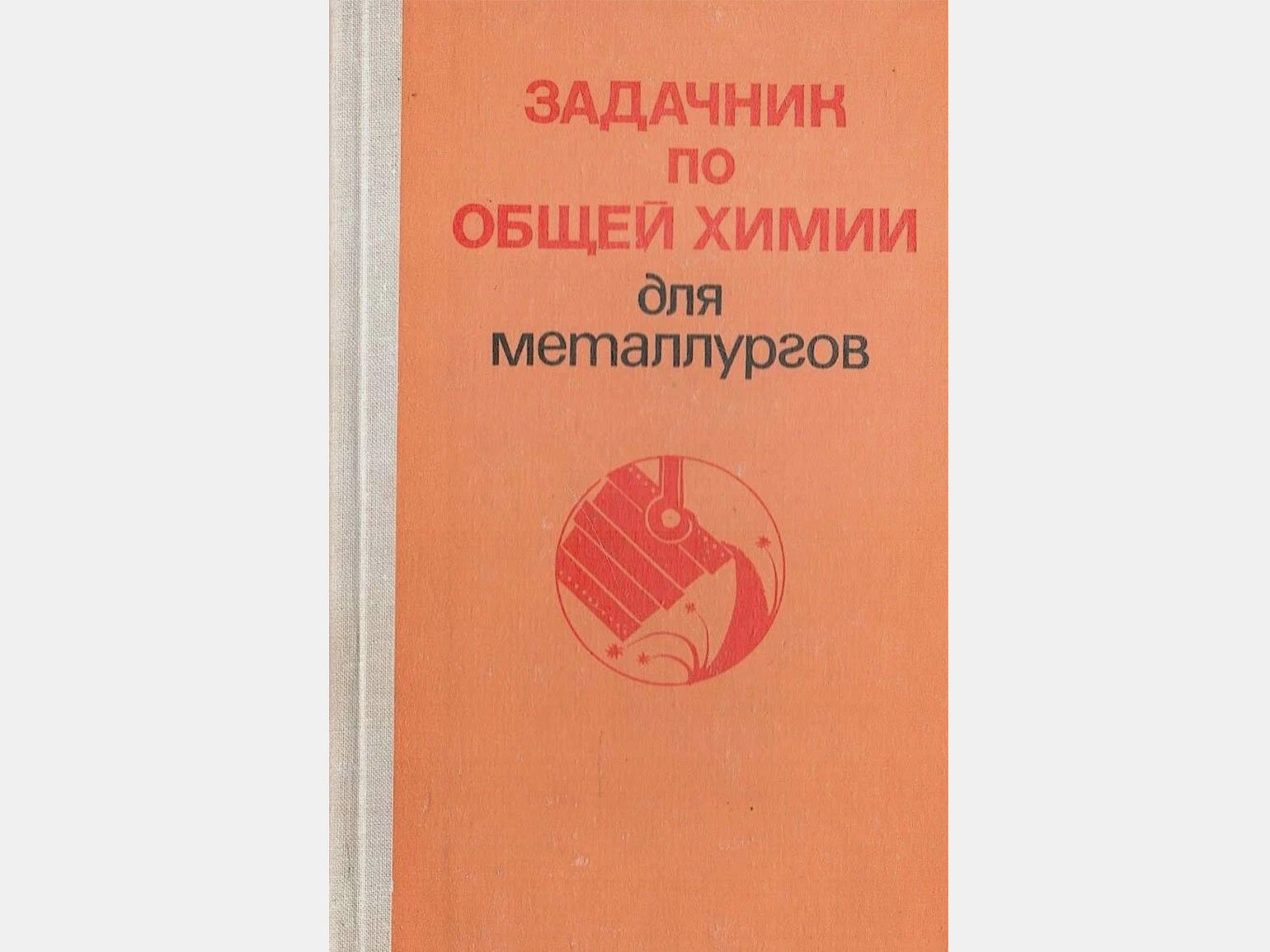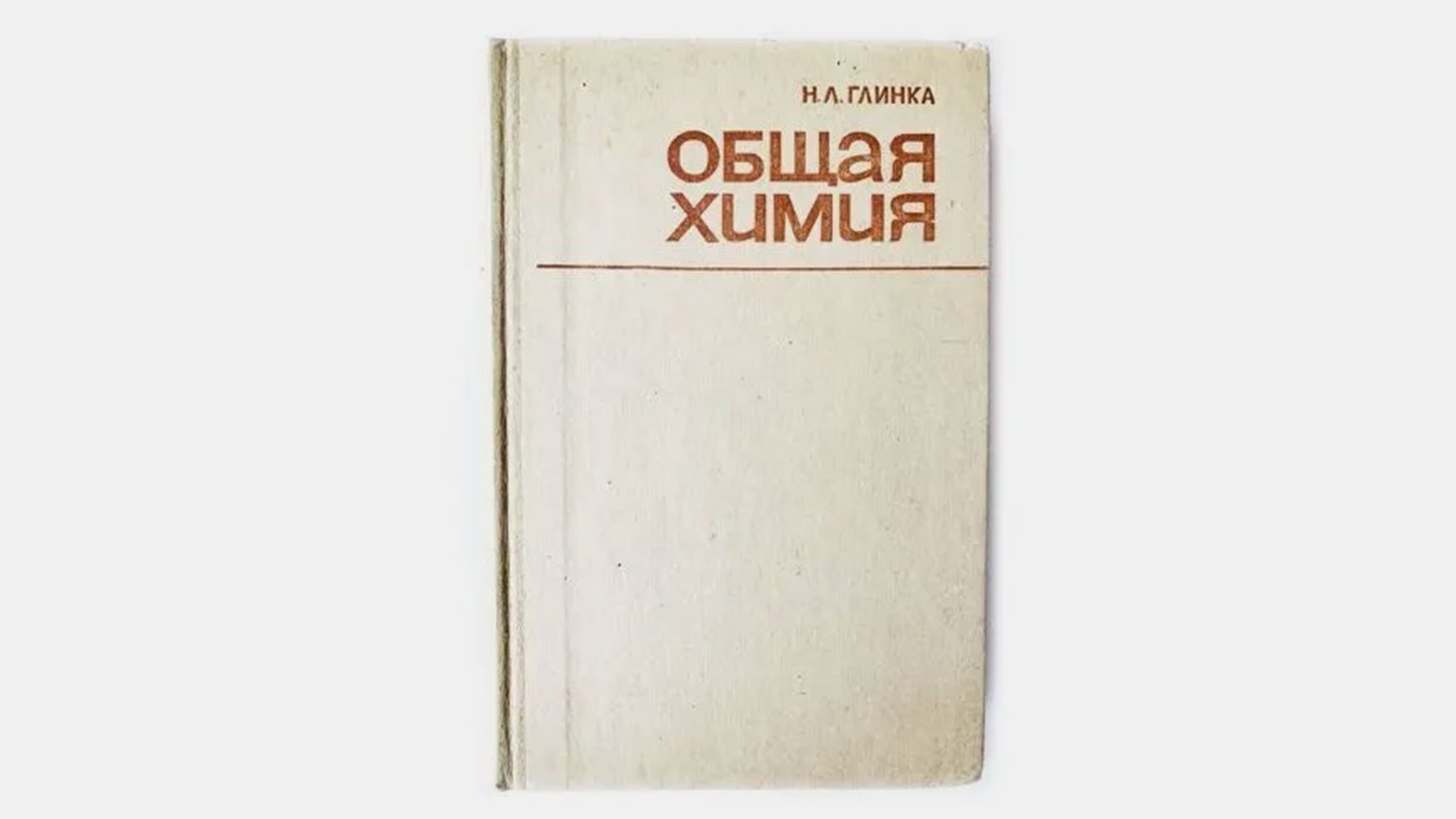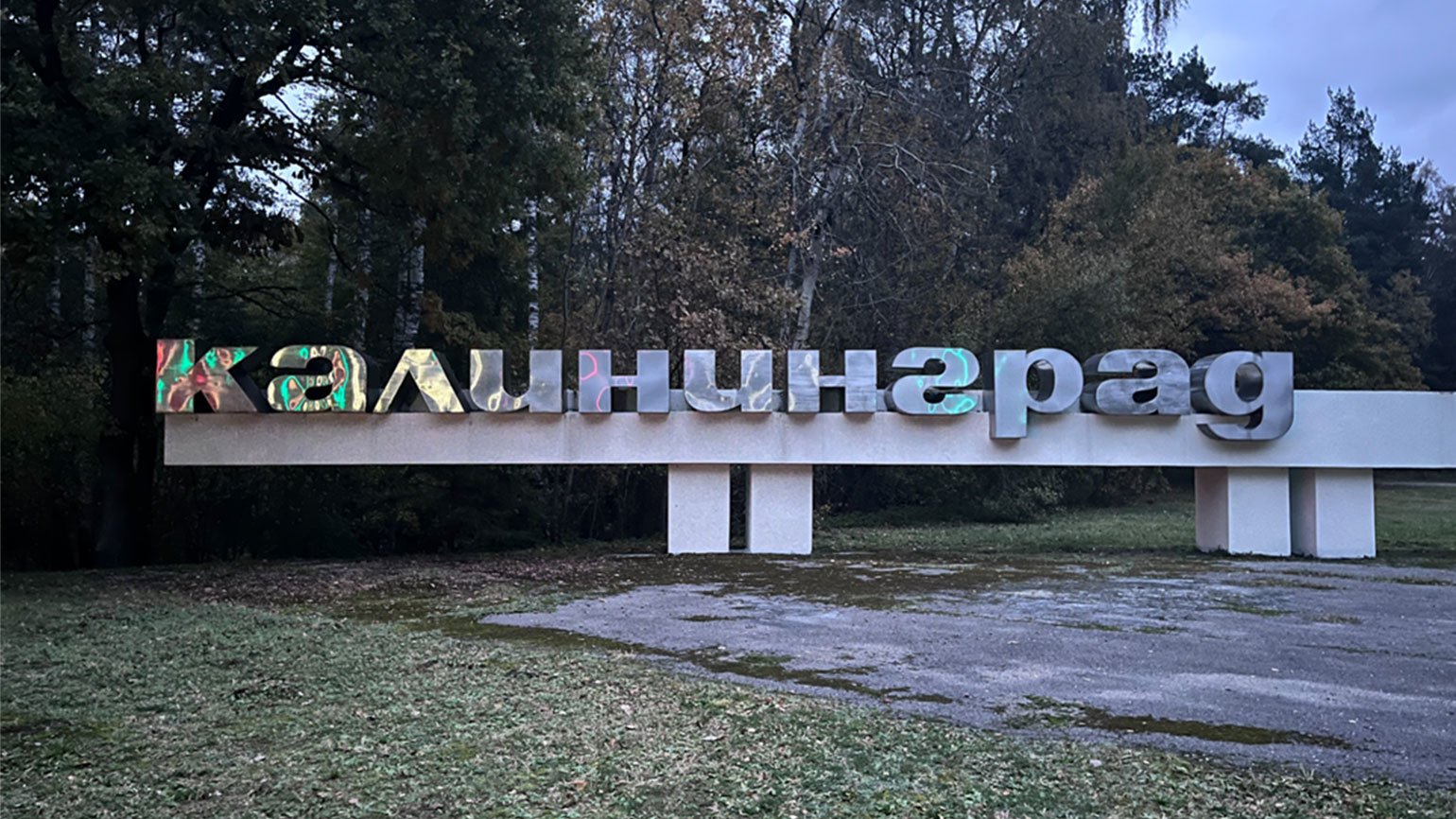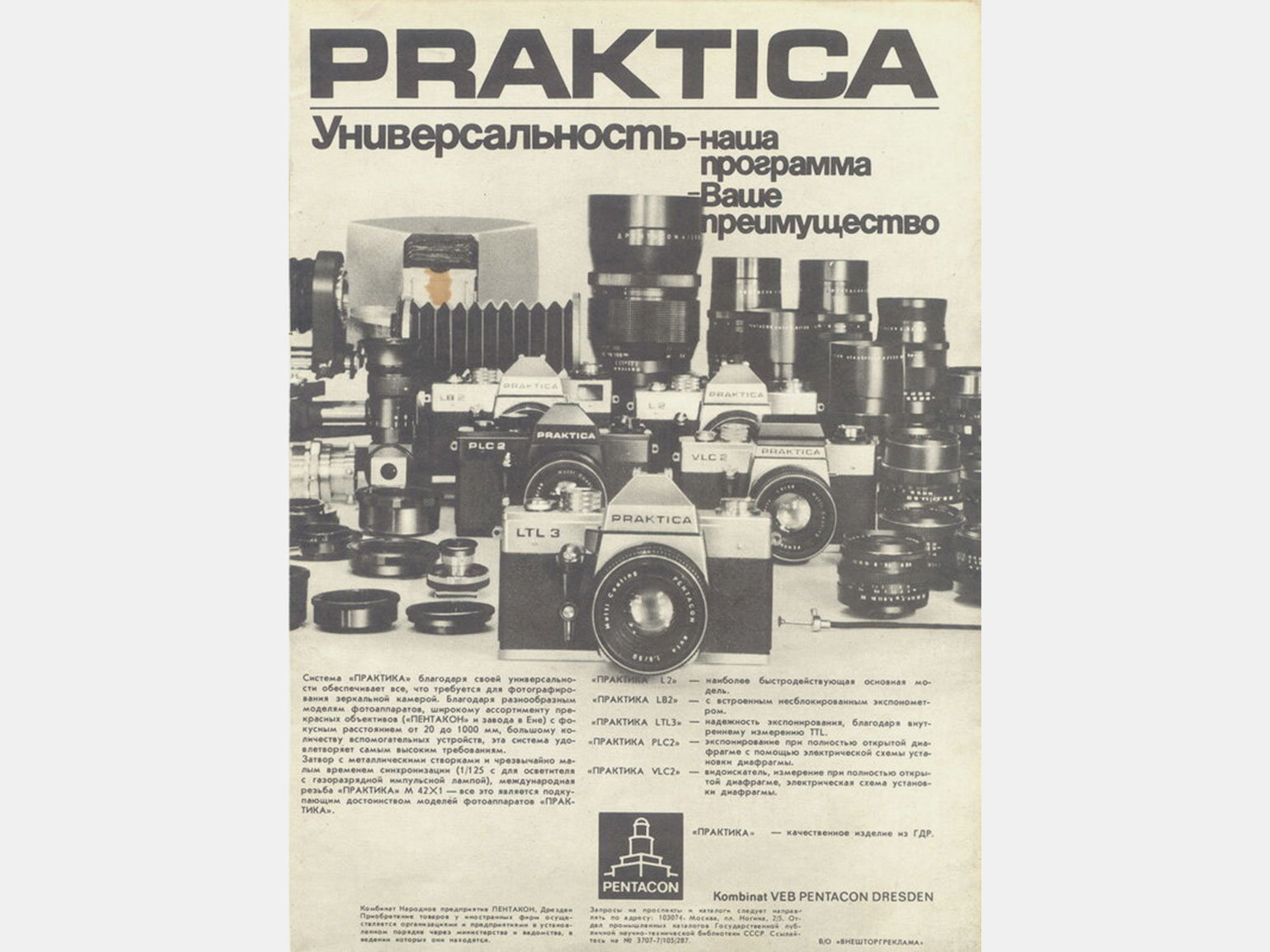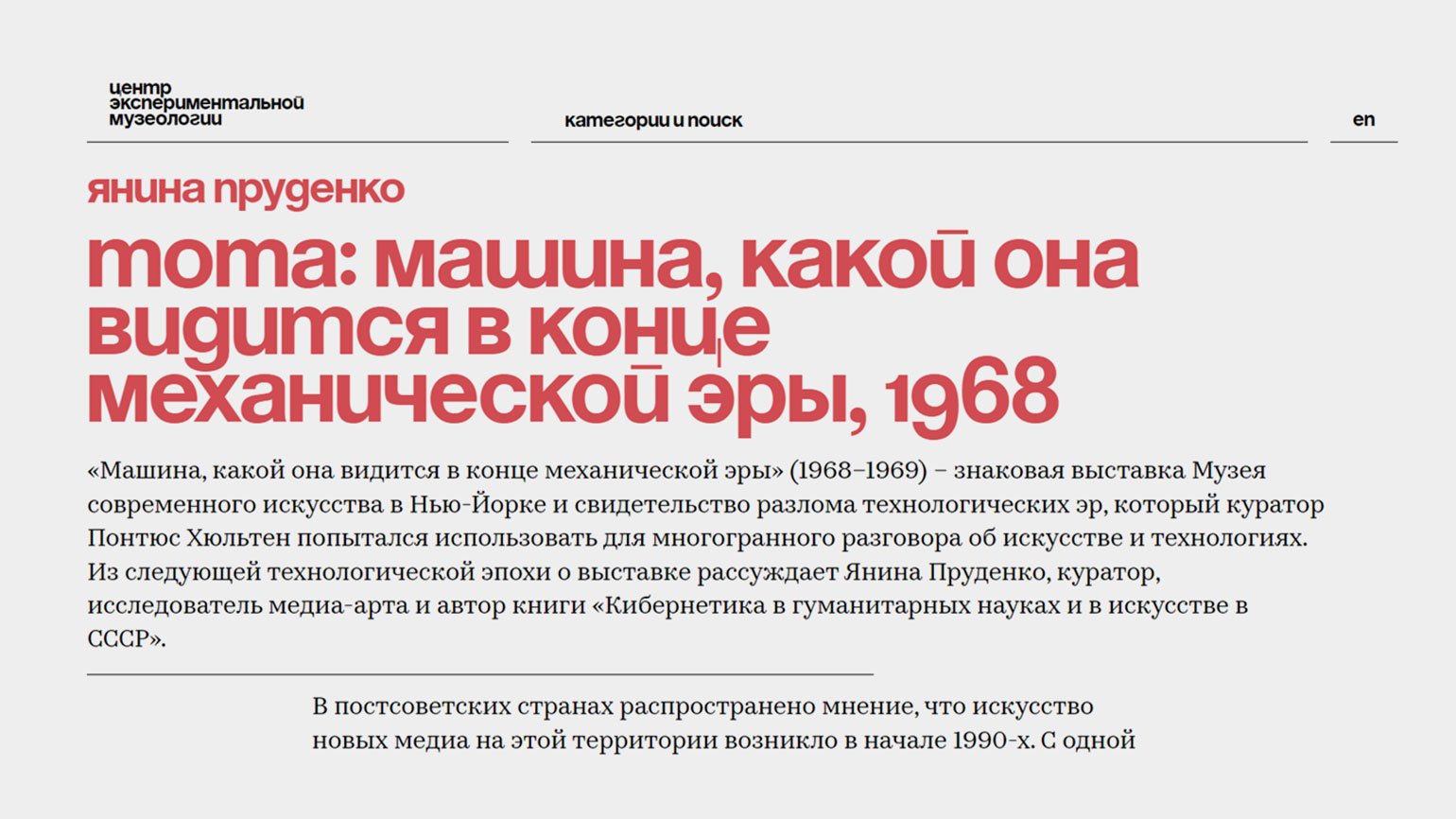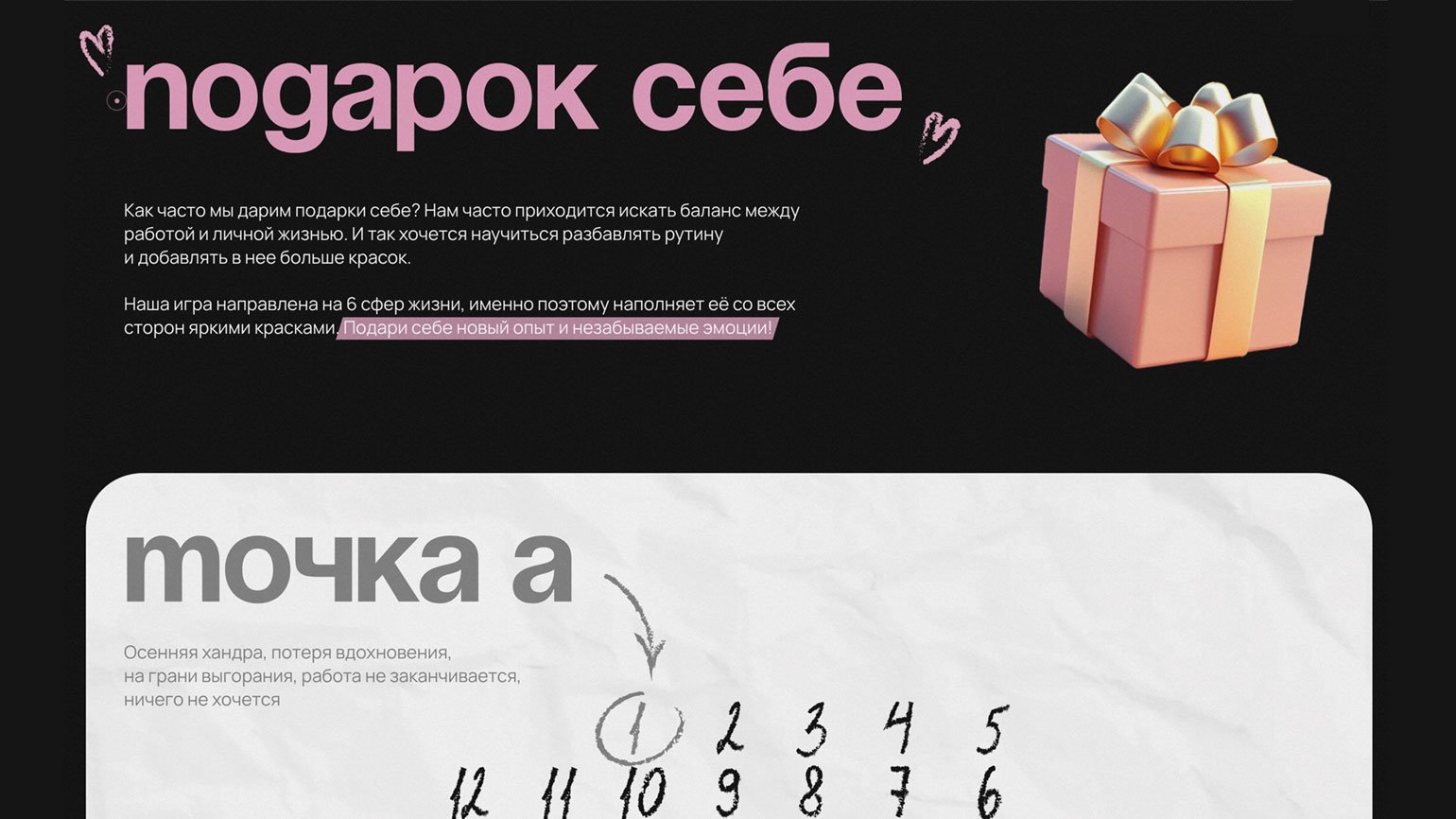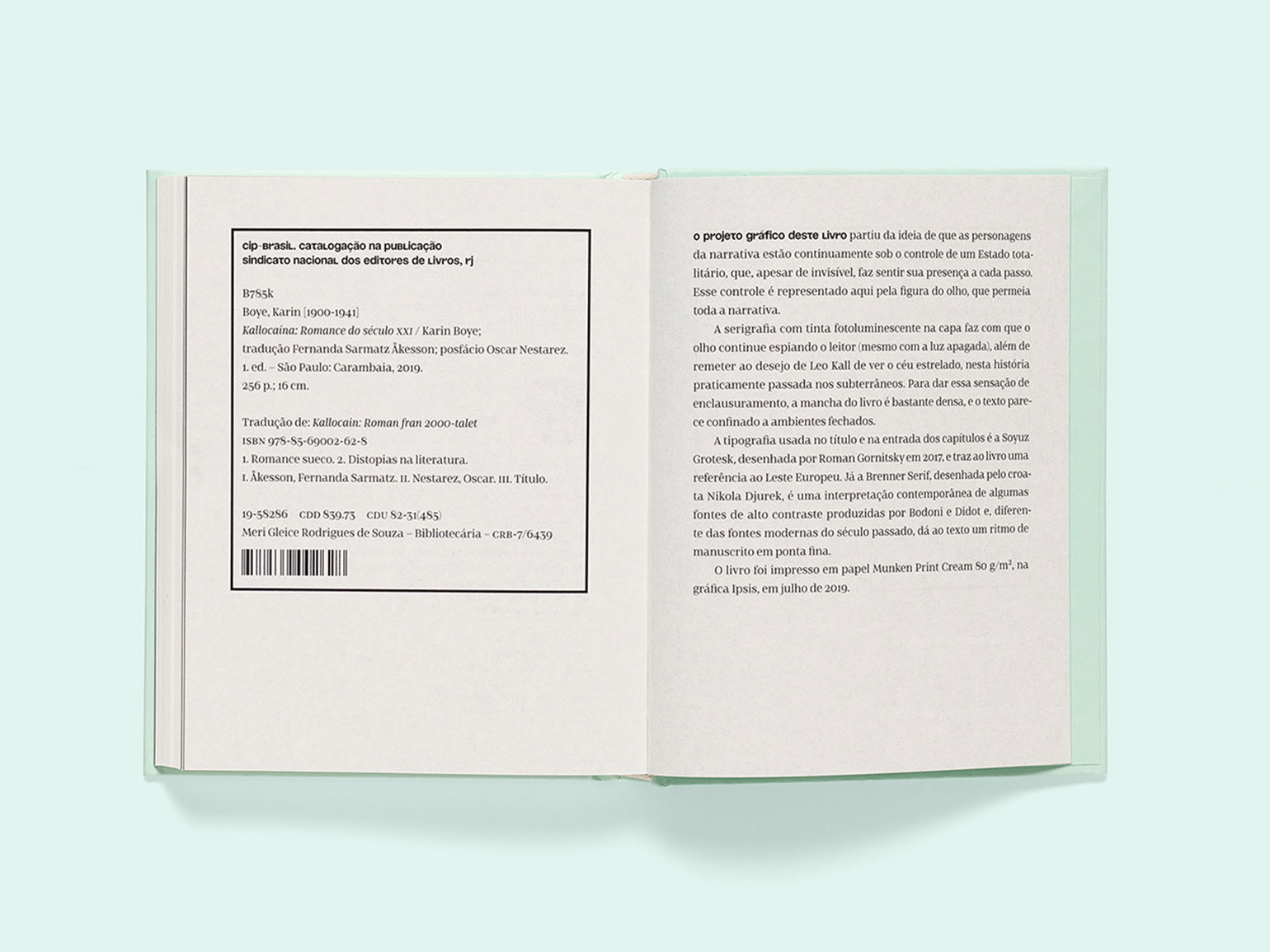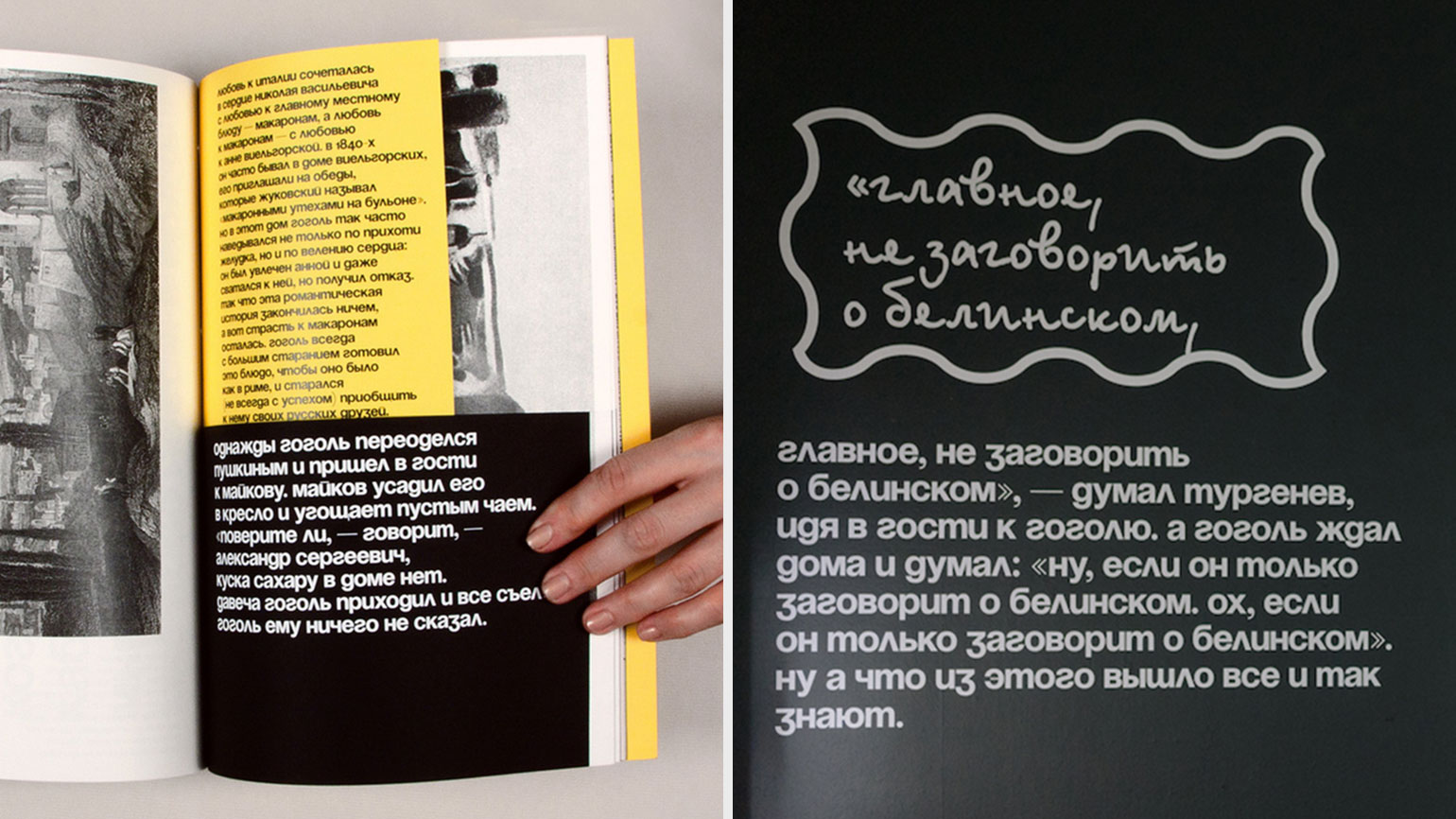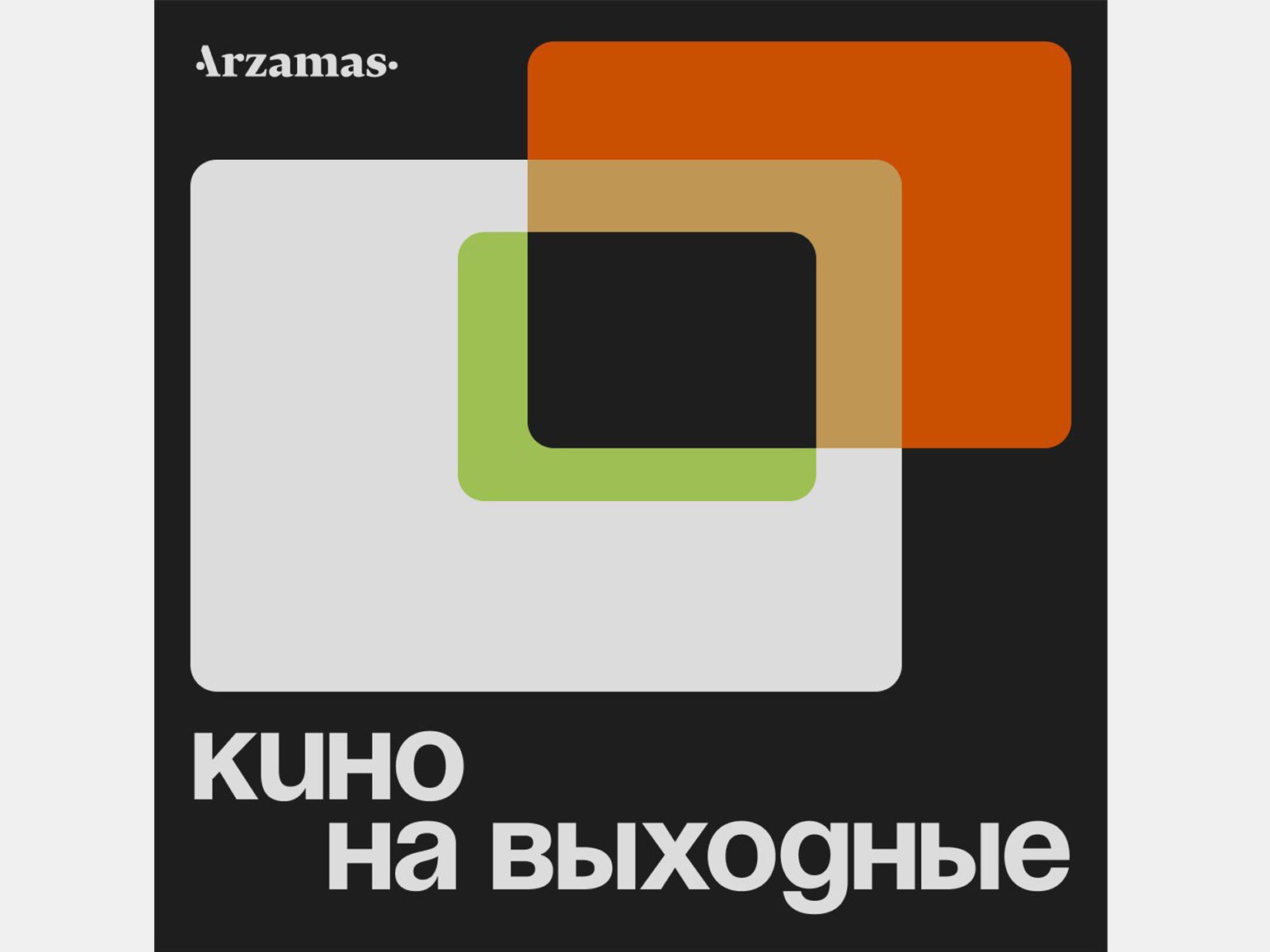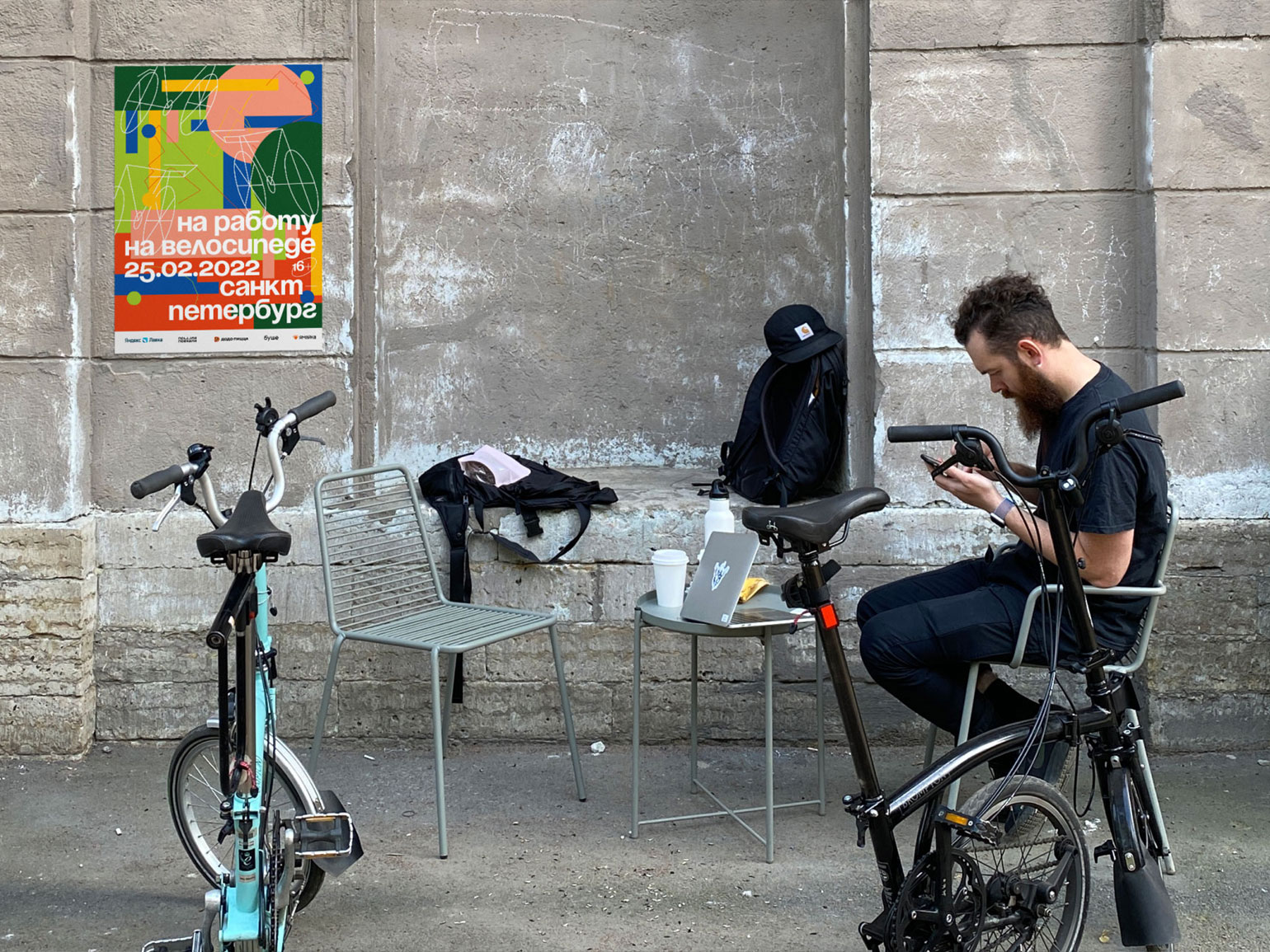
Шрифт Soyuz Grotesk: где используют и с чем сочетают
Рассказываем, для каких проектов подходит Soyuz Grotesk, и показываем примеры шрифтовых пар с ним.
Создать эффектную типографику для сайта, документа, постера или рекламы непросто. Правильное решение очень важно: шрифты влияют на восприятие текста и изображений, они способны и привлекать, и отталкивать. К тому же их много, и даже если для проекта уже выбран основной шрифт, к нему наверняка понадобятся дополнительные.
Разберём модную современную гарнитуру Soyuz Grotesk и расскажем, с чем её сочетать.
Soyuz Grotesk — что это за шрифт
В 2017 году Роман Горницкий выпустил шрифт Soyuz Grotesk. Он опубликовал его как продукт своей студии Typefaces of the Temporary State: название можно перевести как «Шрифты временного государства» или «Шрифты временного состояния». Номинально это оцифрованный шрифт без засечек, который с середины 1960-х и до конца 1980-х был моден в СССР, однако за созданием «Союза» стоит намного более интересная история, чем перевод литер в digital.
В 1963 году два студента Полиграфического института, Юрий Курбатов и Максим Жуков, сконструировали «кириллическую гельветику». В Европе и США к этому времени интернациональный (или швейцарский) стиль уже был широко распространён, а шрифтовые студии и крупные компании создали множество чистых, нейтральных, удобных гротесков. Однако на Западе не работали над кириллическими кассами: из-за изоляции большей части русскоязычного мира такой потребности не было. В странах соцлагеря, в свою очередь, у дизайнеров не было доступа к западным шрифтам. Курбатов и Жуков решили сами создать кириллизированный «советский Neue Haas Grotesk», несмотря на то, что у них не было ни проектировочных документов, ни эскизов оригинальных литер.
Их проект заметно отличался от всего, что использовали советские типографии: для современников шрифт Курбатова и Жукова выглядел необычно, свежо, «по-западному» — и потому стал моден. Однако это даже не был набор в прямом, традиционном смысле: шрифт существовал только в виде фотокопий, поскольку студентам, а впоследствии и молодым специалистам, не дали возможности отправить его в производство.
Особенно меня завораживал процесс выклеивания заголовков. На контрастной фотобумаге печатали шрифтовые наборные кассы, из них вырезали нужные буковки и клеили слова на резиновый клей по едва заметным карандашным направляющим. Потом делали ещё одну репродукционную съёмку, ещё отпечатки и получали оригинал-макет для тиража.
Анна Казьмина,
воспоминание о работе отца-дизайнера, личный блог
Заголовок на обложке книги набран гротеском Курбатова и Жукова. В оформлении видны неровности — вероятно, макет был собран не очень аккуратно
Этот цифровой Neue Haas Grotesk максимально близок к оригинальному рисунку шрифта 1957 года
В 1966 году другой студент Полиграфа, Василий Валериус, переработал дизайн уже на тот момент известного бюллетеня ВНИИТЭ «Техническая эстетика». Вёрстка стала более «швейцарской», а название он набрал советским «нойе хаасом». Именно этот вид обложки и логотипа потом будет долгое время ярко выделять «Техническую эстетику» среди другой периодики в Союзе.
Вёрстка в самом первом выпуске бюллетеня за январь 1964 года и в первом выпуске с новым дизайном в январе 1967-го
Популярность гротеска Курбатова и Жукова в кириллической печати росла. Однако из-за того, что он распространялся только фотокопиями — в отличие от «государственных» гарнитур «Литературная», «Заголовочная газетная» и прочих, — появлялись образцы, стилистически напоминающие этот шрифт.
Пропорции и рисунок некоторых букв на обложке учебника и объёмных знаков на стеле напоминают «советскую гельветику»
Ещё один пример оформления текста гротеском «по мотивам»: в шрифте Курбатова и Жукова не было заглавных букв, для этой рекламы их, вероятно, дорисовали
В 2016 году фонд V-A-C основал платформу «Центр экспериментальной музеологии», где занимаются исследованием музея как институциональной единицы и медиума. Разрабатывать айдентику ЦЭМ пригласили Романа Горницкого, и для этого проекта он решил оцифровать и актуализировать гротеск Курбатова и Жукова. Эта версия шрифта для центра была названа им Aestetica — с отсылкой к «Технической эстетике».
Шрифтовая пара Aesthetica и Kazimir Text в дизайне сайта
Горницкий продолжил изучать тему и работать над графикой кириллической и латинской кассы, и этот проект вырос в Soyuz Grotesk — шрифт без засечек с особенным, узнаваемым визуальным характером и деталями:
• Только строчными буквами и только в солидном начертании Bold.
• R и z, будто нарисованные носителем русского языка, который никогда не видел латиницу и чертит их впервые — например, r как развёрнутую ч. Эти ироничные детали — референс к появлению первой кириллизации «Гельветики», которую создавали в отрыве от латиницы, только наоборот: такой графикой Горницкий показал, как можно латинизировать кириллицу.
• Вертикальными тонкими линиями в й, щ, ц, э и кавычками-лапками из таких же штрихов — ещё тоньше, минималистичнее и чище, чем в проекте советских студентов Полиграфа.
Кириллица и латиница Soyuz Grotesk
Изображение: Skillbox Media
Историю разработки шрифта от самого Романа Горницкого на английском языке можно прочитать здесь.
Посмотрим, как Soyuz Grotesk используют в дизайне сайтов и книг, рекламе и брендинге.
Soyuz Grotesk в дизайне лендингов
Шрифтовая пара из бесплатных Soyuz Grotesk и Raleway придала минималистичному лендингу базы отдыха прогрессивный, но тёплый характер.
Soyuz Grotesk и Raleway
Скриншот: сайт «8 Сосен» / Skillbox Media
Виртуальный павильон России на Венецианском биеннале в 2018 году служил как пространство для независимых проектов. Он был «построен» на платформе Readymag, а для оформления текстов дизайнерка Мария Косарева выбрала свежий на тот момент Soyuz Grotesk — самый русский из гротесков. Такое решение помогло выразить идею пересечения национального и глобального.
Изображение: Maria Kosareva / Readymag
Страница лагеря для взрослых, где занимаются разными видами искусства, оформлена парой из родственных шрифтов Soyuz Grotesk и Helvetica Neue, а контраст им составляет рукописный Gogol.
Шрифтовая пара Soyuz Grotesk, Helvetica Neue, Gogol
Скриншот: сайт «Арт Ретрит» / Skillbox Media
В дизайне лендинга о развивающей игре Soyuz Grotesk с его необычной латиницей символизирует креативность, а нейтральный Manrope успокаивает насыщенный элементами дизайн.
Шрифтовая пара Soyuz Grotesk и Manrope
Скриншот: Contraste Agency / Skillbox Media
Soyuz Grotesk в печати
Kallocain — дистопия шведской писательницы Карин Бойе о «таблетках правды» в тоталитарном государстве. Для оформления основного объёма текста бразильские дизайнеры выбрали современную антикву Brenner, а для заголовков Soyuz Grotesk. Здесь он служит визуальной отсылкой к Восточной Европе.
Шрифтовая пара Soyuz Grotesk и Brenner
Изображение: Alles Blau / Julia Masagão / Behanc
Дизайнерка Наташа Агапова разрабатывала и графическое оформление экспозиции в Доме Гоголя «Верю — не верю», и каталог, который в 2019 году стал победителем премии «Жар-книга». Темой выставки были анекдоты о взаимоотношениях Гоголя и Тургенева, и шрифтовая пара из Soyuz Grotesk и Betina Script визуально поддерживает ироничное настроение.
Soyuz Grotesk и Betina Script в каталоге и оформлении выставки от Наташи Агаповой
Фото: Жар-книга / издательство «Перо» / «Дом Гоголя»
Soyuz Grotesk в визуальных коммуникациях
Фирменные шрифты Arzamas — Formular и Lava, их используют практически во всех каналах академии. Однако в обложке для подборки фильмов дизайнерка Маша Касаткина использовала Soyuz Grotesk, и в композиции с мягкими прямоугольниками винтажных оттенков он создаёт настроение семидесятых.
Изображение: Arzamaz / Telegram
Акция «На работу на велосипеде» проходит несколько раз в год в крупных городах, в том числе в Санкт-Петербурге. Для этой инициативы студия Holystick оформила тексты на афишах и в SMM-графике Soyuz Grotesk, который даже на насыщенном деталями и яркими цветами фоне выглядит заметно.
Фото: Holystick Studio
Soyuz Grotesk в айдентике
Soyuz Grotesk — наследник шрифта с историей и визуальными деталями, которые вызывают определённые чувства у читателей с опытом жизни в СССР. Например, уважение к слову и ощущение, что так оформлены тексты, за которыми стоят учёные и инженеры. Так, студия Electric Red использовала Soyuz Grotesk в дизайне фирменного стиля для Открытого университета Егора Гайдара.
Изображение: Electric Red
Изображение: «Фонд Егора Гайдара»
Кроме того, этот гротеск зрители могут воспринимать как серьёзный, маскулинный. В этом примере исключительно коммерческого дизайна Soyuz Grotesk работает в дизайне айдентики для бренда мужской косметики.
Изображение: Anatolie Micaliuc / Behance
Айдентика кафе грузинской кухни в квартале Flacon — «Хлебозавод» в Москве построена на основе Soyuz Grotesk. Благодаря этому бистро выделяется среди модных заведений: шрифт способен вызывать ностальгию по временам доброго советского кино и при этом выглядит современно и ясно.
Фото: «Грузинское бистро YUG»
Больше примеров Soyuz Grotesk в рекламе и размышления о его популярности — в посте Маши Троицкой.
Где скачать Soyuz Grotesk
Soyuz Grotesk в единственном начертании Bold распространяется только бесплатно. Шрифтовые файлы можно скачать на разных агрегаторах, но лучший способ — на сайте Typefaces of The Temporary State. Так вы гарантированно получите правильный, качественный ZIP-архив.
Шрифтовая пара Soyuz Grotesk и Manrope — оба шрифта бесплатные
Скриншот: сайт oliiji / Skillbox Media
Альтернативы Soyuz Grotesk
С одной стороны, у Soyuz Grotesk нет близких аналогов. Это шрифт с особенным визуальным характером и необычной логикой в графике. С другой стороны, он производная от великого Neue Haas Grotesk, поэтому можно обратиться к другим гротескам интернационального стиля:
• Pragmatica — первая настоящая кириллическая «гельветика».
• Aktiv Grotesk — нейтральный, но строгий гротеск. Его можно активировать с подпиской Adobe Creative Cloud.
• Neue Montreal — семейство современных шрифтов без засечек, которые отлично подходят для digital-дизайна.
• Unica77 — гибрид трёх шрифтовых столпов: Helvetica, Akzidenz-Grotesk и Univers.
• Rubik Bold и Extra Bold — именно в полужирном и жирном начертаниях можно увидеть подобие «Союзу».
• Didact Gothic — с Soyuz Grotesk его роднит форма t.
Логотип оформлен Soyuz Grotesk, и рядом с Helvetica Regular он выглядит акцидентным